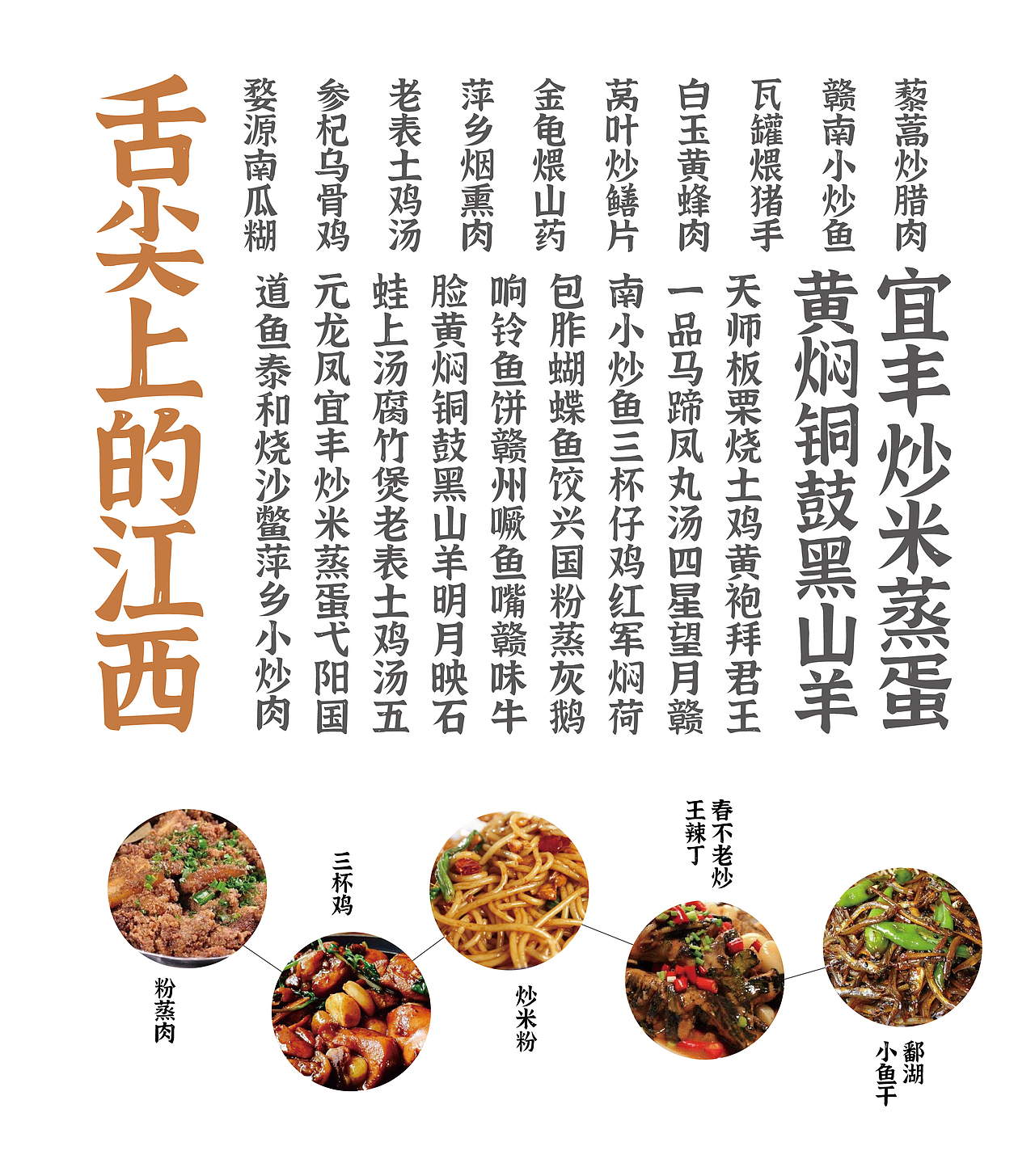
我的首套字库江西拙楷正式跟大家见面了,免费商用!
大家好,我是黄煜臣,我个人第一套字体,今天正式跟大家见面了。第一套字体的发布我很重视,自己花了那么大精力去做这件事,今天终于有了一个阶段性成果,此时内心既有点小激动还有些忐忑,我不知道发布后会有什么效果,大家是喜欢还是无感?会不会带着期待而来,又失望而去?不过俗话说的好,丑媳妇终得见公婆,藏着掖着不敢露脸肯定是不行的,敢于直面不同眼光的评判才是勇敢者的做法,说不准会有人喜欢这个丑媳妇。
这是一套手写楷体,相比电脑中标准化制作的楷体,这套字体的笔画会带有一些书写的痕迹,每个字的笔画是没有统一标准的,所以看上去显得不够规范,但是会有一种手写的自然之感。这套字体从写手稿开始到今天的最终成品,前前后后花了近半年时间,仅仅是调节点,就花了20多天,其中的滋味做过才知道。
这套字体从手稿到成品,中间经过了无数次的修改调整,与最初字形相差挺大。对于这款字体的发布,我不希望仅仅就是一款字体的展示,我希望它能发挥更大的作用,带来一些其他的价值,为了达到这个目的我想了很久——最终决定用这款字体为我们大江西做宣传。江西在各省市一直是一种低调的存在,不管是经济发展还是对外传播都是比较滞后的,我作为江西人,现在还没有能力用真金白银去为家乡做贡献,但是我可以用我的一点专业技能来为江西打打广告,做做宣传,希望让更多人认识他,喜欢他。
<br>话不多说,我就用这款字体来粗浅的介绍一下我的家乡——江西的山和水,这里的城市和人文。
江西是中国森林覆盖率排第二的省份,达到了60%以上,一跨进江西的大门,扑面而来满眼都是绿,堪称天然大氧吧。这里的山,各有特色,高,奇,险,峻。这里的水,清澈干净,烟波浩渺。看惯了外面的灯红酒绿,游遍了现代的都市街区,来我们江西看看山,玩玩水,还有什么比这更惬意事情呢?我相信,你来了就不想走了。
我们江西的城市,可能很多你都没有听说过名字,它们没有大城市的繁华,灯光不够绚丽,大楼不够高耸,只有小家碧玉的烟火气,它们偏于江南一隅有点不够起眼。不过你们在这里可以逛一逛街道,尝一尝街边的美食,感受一下江西老表们恬静的城市生活。
上面展示的都是我们江西的古代先贤,近现代江西也出了很多人物,比如方志敏,吴有训,张国焘,陈三立,贺子珍,古柏,陈寅恪...,这些名字像一颗颗明星闪耀在中国的历史天空上。现代最著名的人物当属“魔稻祖师”袁隆平,他低调到让我们江西人都不知道他也是江西的,他绝对是我们江西值得骄傲的一张名片。
江西的美食你现在只能对着这些字看看了,我也只能笼统的报一下我们江西的菜名,要想真正感受一下江西的美食风味,我还是希望你能亲自来一趟,切身实地的体验一下舌尖的刺激。
<br>好了,上面就是对江西一个大概的介绍,我还做了一些字体在包装海报上的应用效果,请看下面<br>
四特酒是我们江西最有名的酒,我们那边办酒席,很多都是用这款酒,当然这个包装我只是展示字体用的,不要当真。
万年贡米,不知道你们听说过没?在我们江西可是大名鼎鼎,自南北朝时期就是皇家贡米。它只生长在万年县山脚下不足300亩的稻田里,亩产只有300斤。可想而知,这款米是有多么精贵和稀缺啊。
乐平桃酥,是我小时候最喜欢的美味,逢年过节,必定会送乐平桃酥。香酥爽脆,味道真不赖啊,回想起来打着这行字的时候我都忍不住要流口水。
江西还有很多好吃的,我就不一一举例了,你们来江西,带些正宗的江西特产回去,一定会有满满的收获。
上面是字体在海报上的应用
这是英文字体展示。
你也可以试试用这个字体来做印章,会有意想不到的效果。跟印章的斑驳肌理很契合。
可以试试用在文创产品上, 比如帆布袋,手机壳。
<br>上面就是我这次发布的新字体这款字的性格和江西很像,   低调内敛,朴实无华毫不张扬,就命名为江西拙楷,希望通过这套字体让江西增加点曝光度,让更多人了解江西。